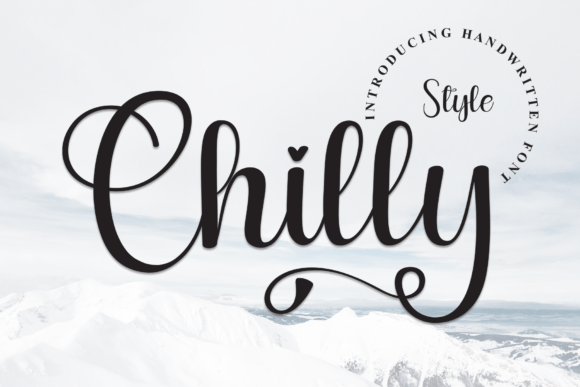
أضف لمسة من الإبداع والتميز إلى تصميماتك مع Chilly Font!
هذا الخط الرقمي الفريد يجمع بين الأناقة والبساطة، مما يجعله مثاليًا لمجموعة متنوعة من المشاريع التصميمية.
مميزات الخط:
- تصميم فريد وعصري: يتميز بمظهر نظيف وجذاب يناسب جميع أنواع التصميمات.
- متعدد الاستخدامات: مثالي للشعارات، العناوين، بطاقات الدعوة، المشاريع الرقمية، والمطبوعات.
- سهولة التخصيص: يتماشى بشكل رائع مع مختلف الألوان والأساليب الفنية.
- دقة عالية: يقدم تفاصيل واضحة تضيف لمسة احترافية لتصميماتك.
لماذا تختار Chilly Font؟
- يجعل تصميماتك تبدو أكثر جاذبية وإبداعًا.
- يناسب المصممين المبتدئين والمحترفين على حد سواء.